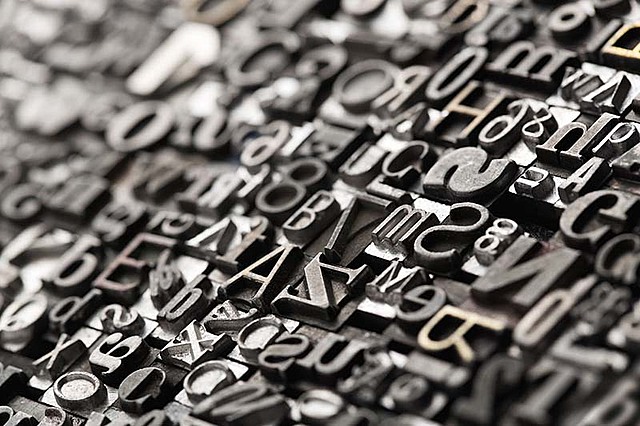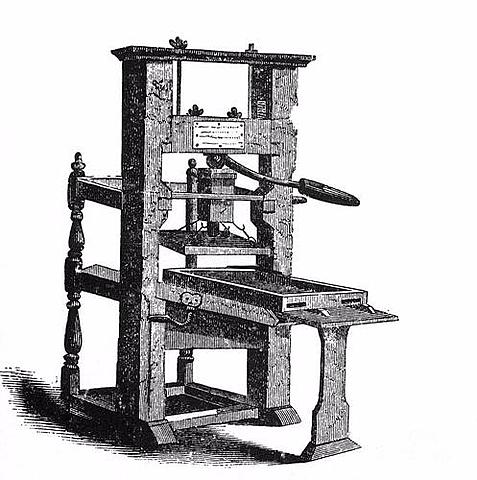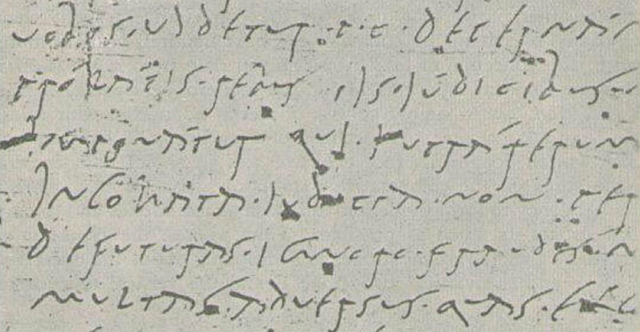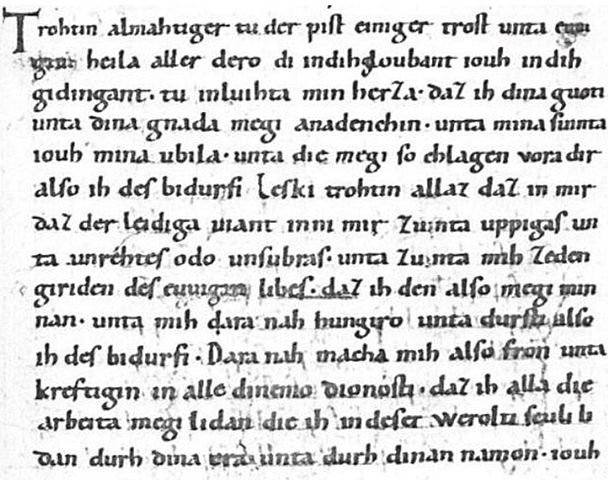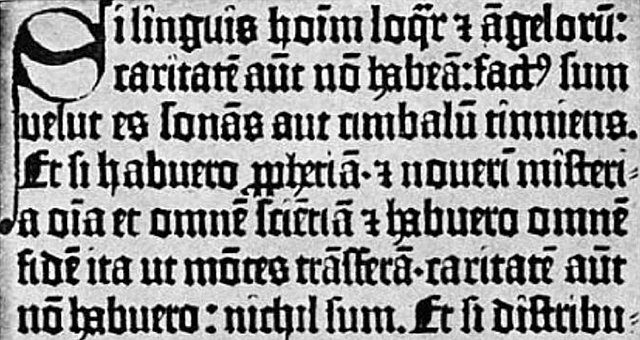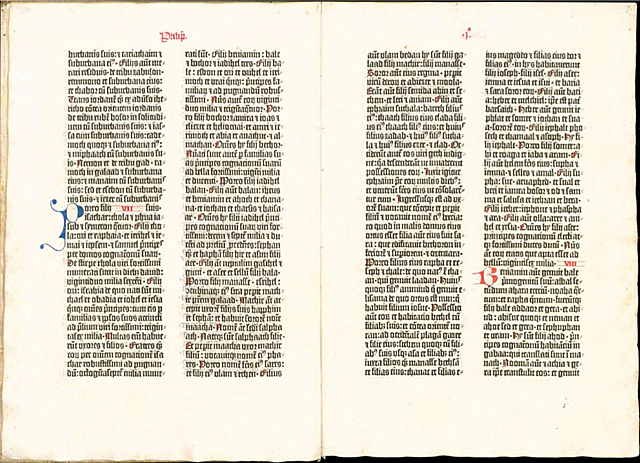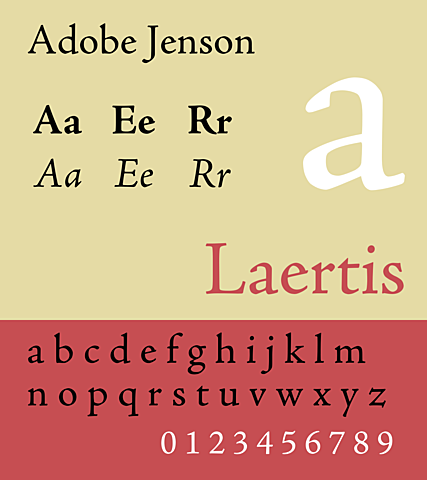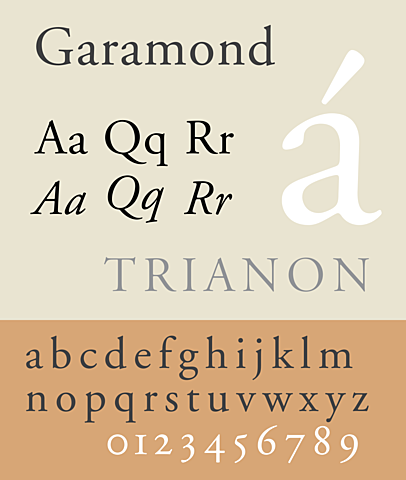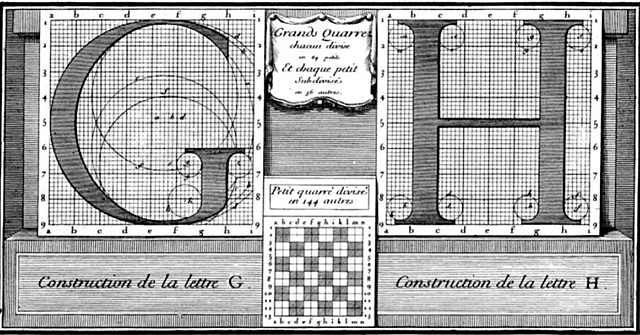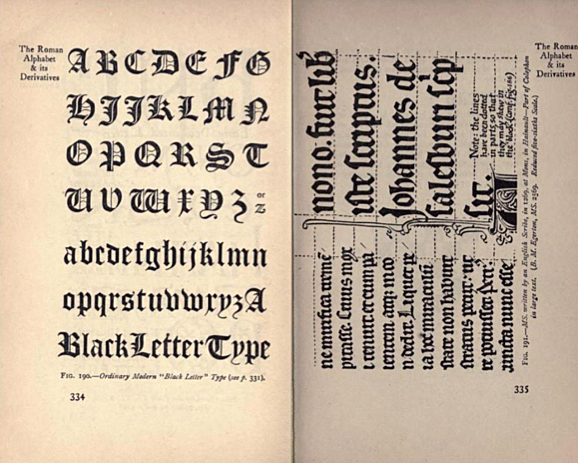
Tra il 41 e il 50 a.C
Testo scritto dell’XI secolo di un monastero benedettino in Baviera, accreditato al monaco Otloh dell’Abbazia di Sant’Emmerano
Nel XV secolo, in Germania si usavano i caratteri gotici.
Caratteri come Blackletter e Jenson ma anche Garamond e Caslon di cui parleremo più avanti, vengono inseriti nella stessa categoria, quella dei caratteri old style.
Johann Gutenberg costruì la prima macchina che permetteva la stampa a caratteri mobili.
Il primo progetto tipografico in larga scala fu la Bibbia di Gutenberg del 1455, detta anche Bibbia a 42 line (B 42), perché stampata, su 42 linea di testo con font: blackletter.
Nicolas Jenson inventò in primo carattere tipografico con caratteri “romani” dopo la scoperta dell’invenzione di Gutenberg.
Aldo Manunzio e Francesco Griffo introdussero il cosiddetto “italic”: corsivo per stampare le opere di Virgilio.
Carattere realizzato dal tipografo francese Claude Garamond nel XVI secolo, agli albori della tipografia.
Tipici del periodo storico culturale dell’Illuminismo.
I caratteri transizionali portarono grandi cambiamenti alla tipografia. -
Il primo transizionale, commissionato nel 1692 da re Luigi XIV di Francia e considerato come un punto di svolta nella storia della tipografia fu il Romain du Roi, il romano (inteso come carattere scritto con l’alfabeto latino) del Re.
Carattere realizzato da William Caslon, inserito fra il Garalde o romani antichi.
È fortemente affine alle tendenze del barocco inglese e olandese dell’epoca in cui venne creato (inizio del settecento). -
Alcuni studiosi di Oxford che, commissionarono alla fonderia di William Caslon di creare un carattere tipografico per l’alfabeto etrusco in modo da studiarne meglio i collegamenti con quello latino.
Progettato nel 1757 dal geniale tipografo inglese John Basketville, è il transizionale per eccellenza.
È uno dei font più apprezzati ed utilizzati da designer e tipografi di tutto il mondo. -
Carattere realizzato dal tipografo francese Firmin Didot e al suo Didot, Un insieme di caratteri che vide per la prima volta la stampa nel 1784.
Carattere dei Bodoniani -
Carattere realizzato da Giambattista Bodoni, che vide la sua prima apparizione nel 1798 e che ancora oggi risulta essere tra i più apprezzati ed utilizzati in tutto il mondo occidentale.
Carattere dei Bodoniani. -
Detti anche Romani Moderni. ITransizionali si chiamano così proprio perché fanno da transizione fra i romani antichi e romani moderni.
I caratteri Sans serif creati tra il Diciannovesimo secolo e i primi due decenni del Ventesimo, prendono il nome di Grotteschi.
Con i bodoniani, ai primi decenni dell’ottocento, siamo in piena rivoluzione industriale.
Sono definiti egiziani perché all’epoca in cui inizialmente apparvero l’antico Egitto era parecchio di moda. -
Creazione del primo font Slab Serif, l’Antique.
L’Akzidenz, è stato sviluppato tra il 1896 e il 1899 da progettisti e incisori anonimi tedeschi per la fonderia Berthold, è uno dei caratteri più importanti e sottovalutati della storia della tipografia.
Edward Johnston, un artigiano e calligrafo, iniziò una personale ricerca sulla buona progettazione tipografica che culminò con la pubblicazione del manuale ”Writing & Illuminating & Lettering”, considerato da li in avanti come una delle pubblicazioni fondamentali per ogni appassionato di lettere e calligrafia.
Johnston accettò l’incarico assegnatogli dalla Westminster Press di progettare i caratteri per la metropolitana di Londra, creando il Jean Sans.
Carattere realizzato da Eric Gill, collaboratore di Johnston.
Utilizzato per la prima volta in un’insegna progettata per un bibliotecario di Bristol. -
Carattere realizzato in Germania, è definito pulito, elegante e geometrico. È considerato capostipite dei caratteri Sans Serif geometrici.
Il quotidiano The Times invitò Stanley Morison, della fonderia Monotype, a mandare le sue proposte relative al design del giornale.
Il TNR divenne subito molto apprezzato ed iniziò ad essere utilizzato anche da moltissimi editori di libri e quotidiani. -
Dopo qualche decennio cadde in disuso, ma torno a diffondersi grazie all’apparizione nei primi computer Apple, e successivamente apparirà anche su dispositivi Microsoft per quasi vent’anni. Diventò probabilmente il fondo più utilizzato della storia.
Realizzato dalla Monotype nel 1934.
Carattere realizzato dalla Scuola Svizzera con l’avvicinarsi dell’era digitale. È definito: pulito, efficiente e moderno; Beatles dei font; il blue jeans dei font. È stato utilizzato per la creazione di molti loghi.
Carattere progettato dal designer svizzero Adrian Frutiger per la fonderia francese Deberny & Peignot, fu uno dei primi esempi di famiglia di font.
Carattere realizzato da Susan Nobrega e poi ripreso da Adrien Frutiger per le macchine da scrivere IBM.